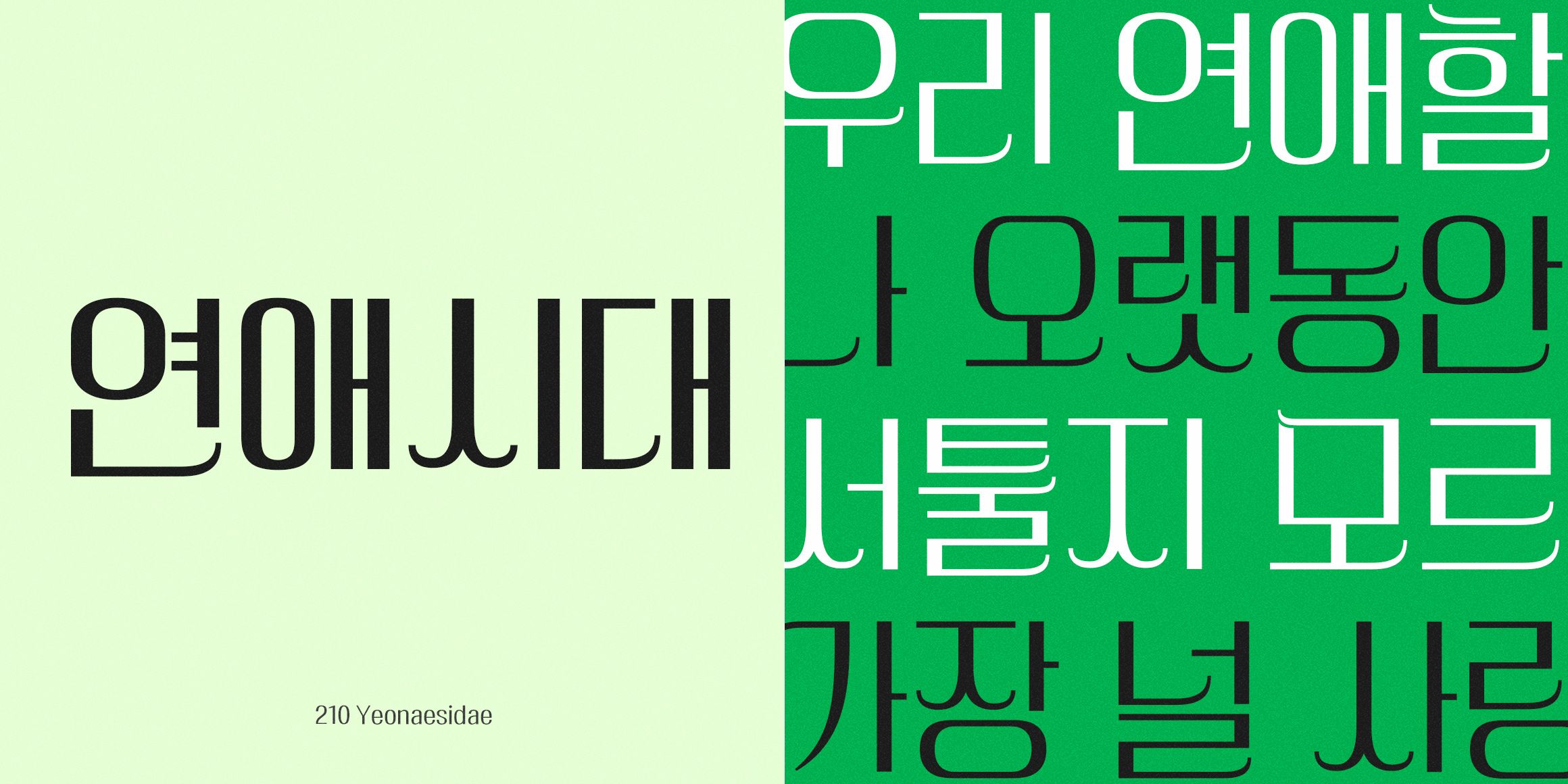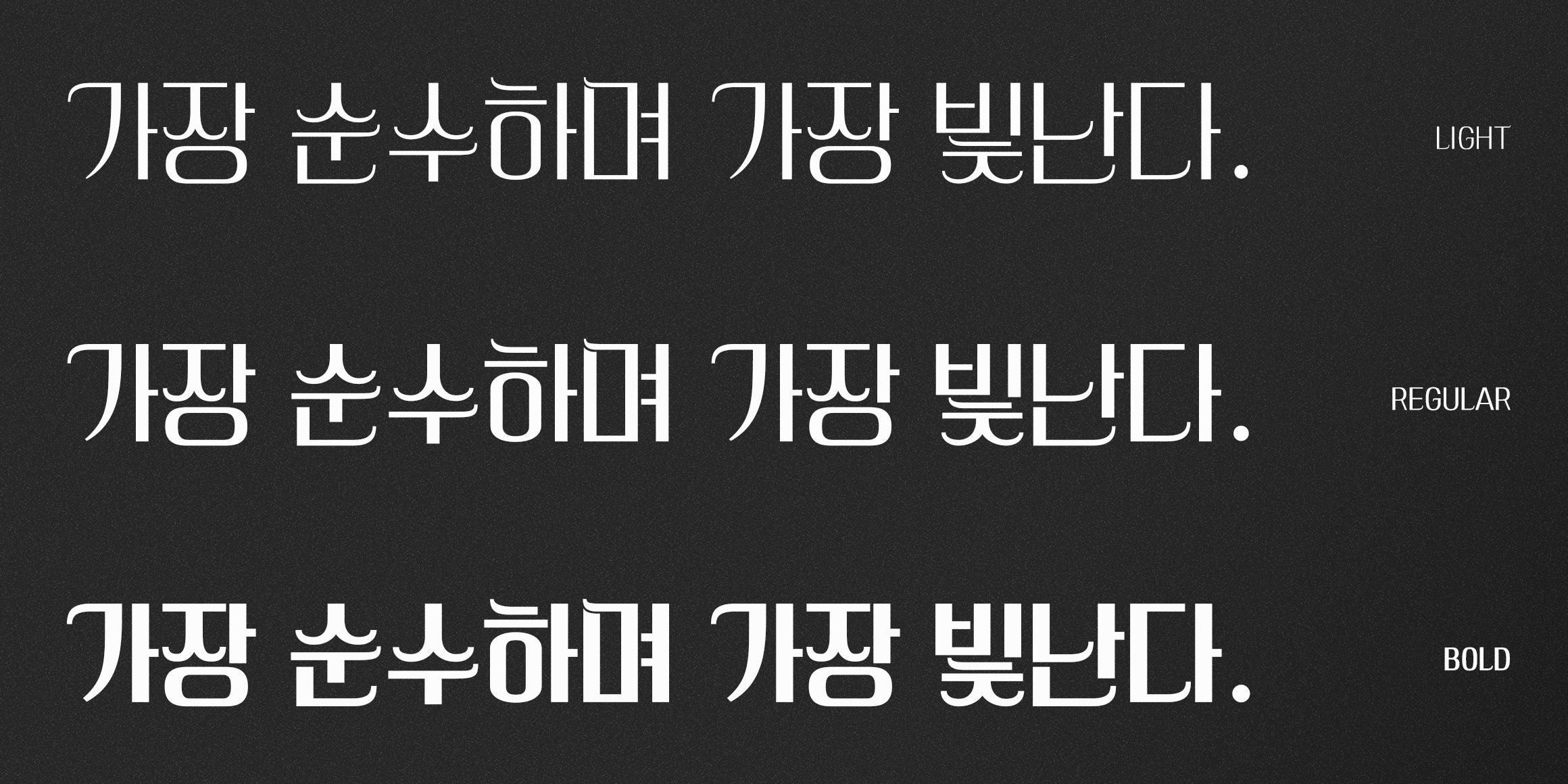
연애시대
레트로 로맨틱 무드
레트로 로맨틱 무드를 불러일으키는 디스플레이 서체로, 부드러운 곡선과 살짝 기울어진 획이 서정적이고 사랑스러운 분위기를 연출합니다. 카페 로고, 커플 굿즈, 이벤트 포스터 등에 활용해 설렘을 강조하거나, 감성 에세이와 상품 패키지의 타이틀로 사용해도 탁월합니다. 빈티지하면서도 현대적인 매력을 동시에 담고 있습니다.